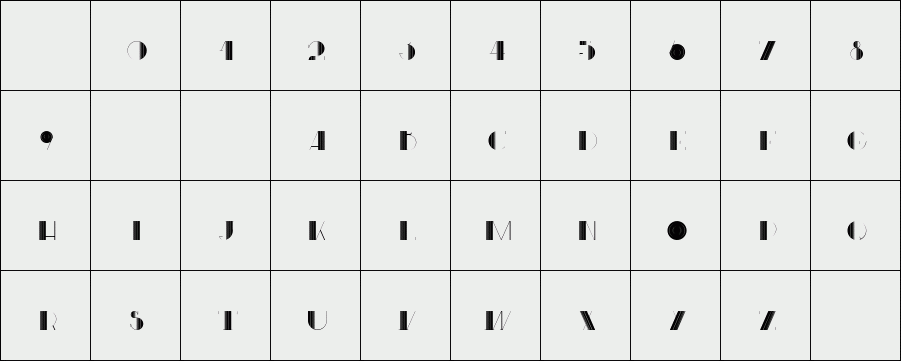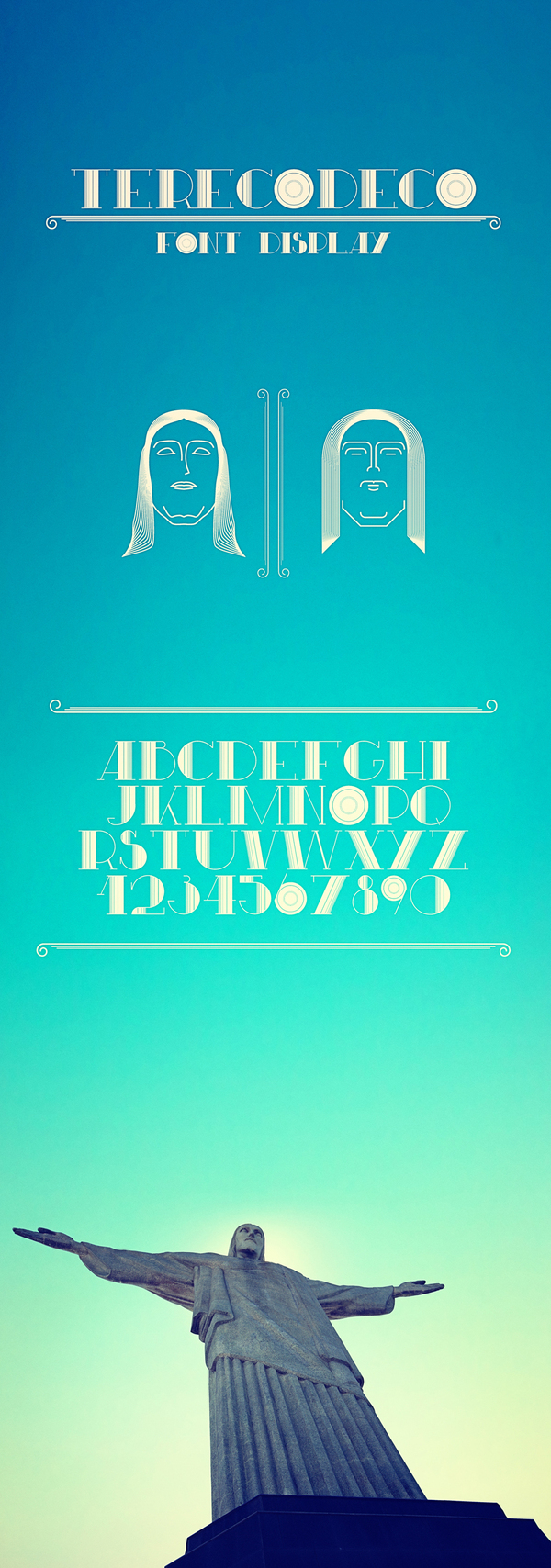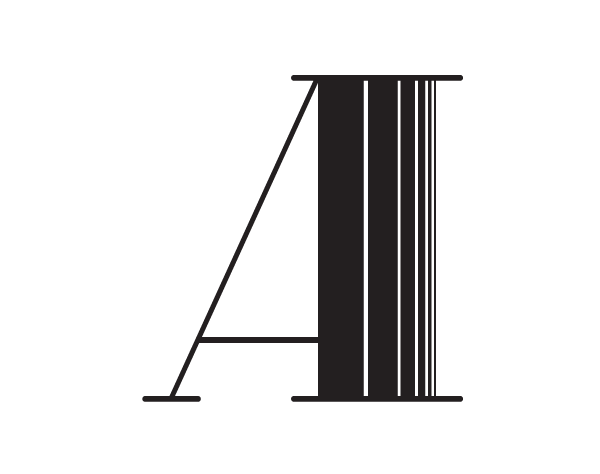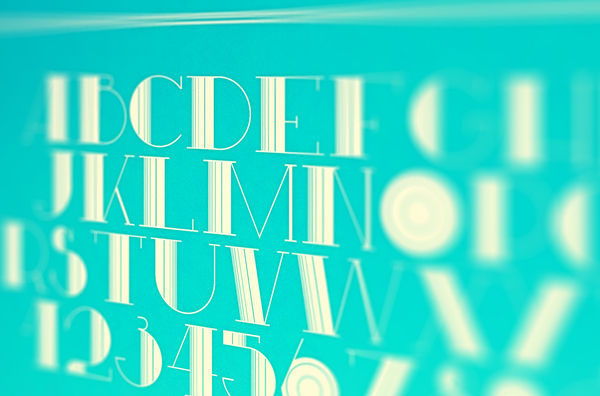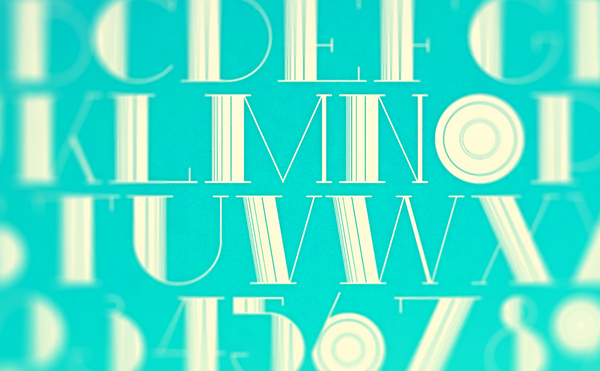
Terecodeco Display
/ Terecodeco
Estudo de fonte com tema Art Déco onde me identifico pelo conceito, uma mistura de vários estilos procurando inovação. É assim que sigo com meus projetos pessoais, sempre tentando elaborar e me arriscar com novos estilos. A composição com o Cristo Redentor é uma forma mais simples de mostrar qual o conceito por trás dessa experiência, o Cristo é a maior escultura ja feita nesse estilo.
Font study with the theme Art Déco, which I identify myself because of the concept, a mix of various styles looking for innovation. This is the way I keep going with my personal projects, always trying to elaborate and take chances with new styles. The composition with the Cristo Redentor, is a sample way to show the concept behind this experience, the Christ, it's the bigger sculpture that's ever been made in this style.
Designer: Du Beluco